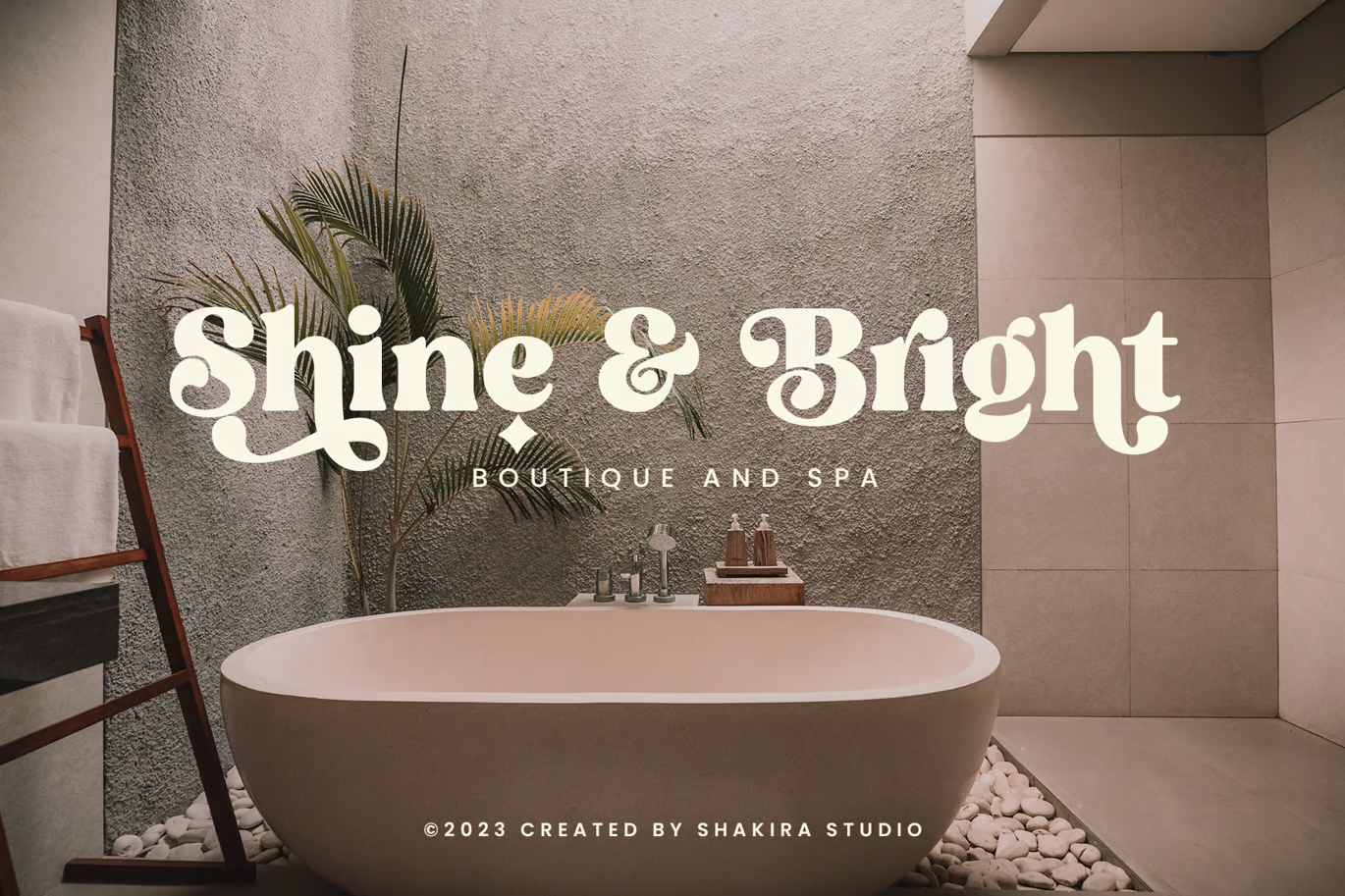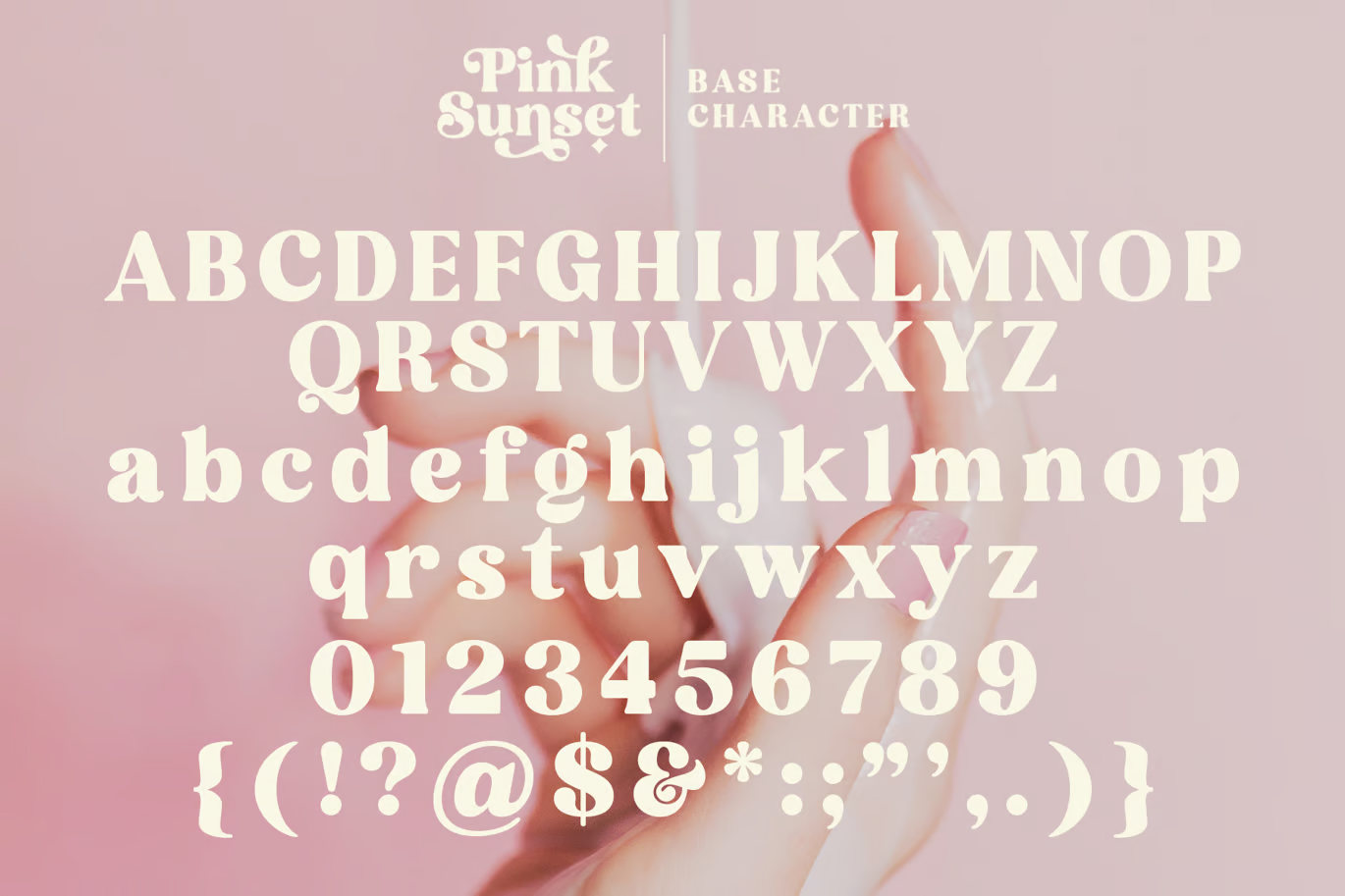
Pink Sunset Font
Description de Pink Sunset Font
La police Pink Sunset est une police moderne avec une touche de style rétro en devenir. Créez de beaux titres accrocheurs et des designs élégants avec une touche de style rétro à l’aide de cette police fonctionnelle. Ses bords droits et ses extrémités arrondies le rendent idéal pour les logos, les cartes de vœux pour des occasions spéciales, les invitations de mariage, les dictons, les publicités et bien plus encore.
Cette police intègre plus de 50 alternatives et ligatures différentes qui vous aideront à créer des logos individuels et nostalgiques, des cartes de visite et bien plus encore. Cela fait de Pink Sunset une police vintage idéale pour tous vos besoins de conception après avoir inclus la version italique.